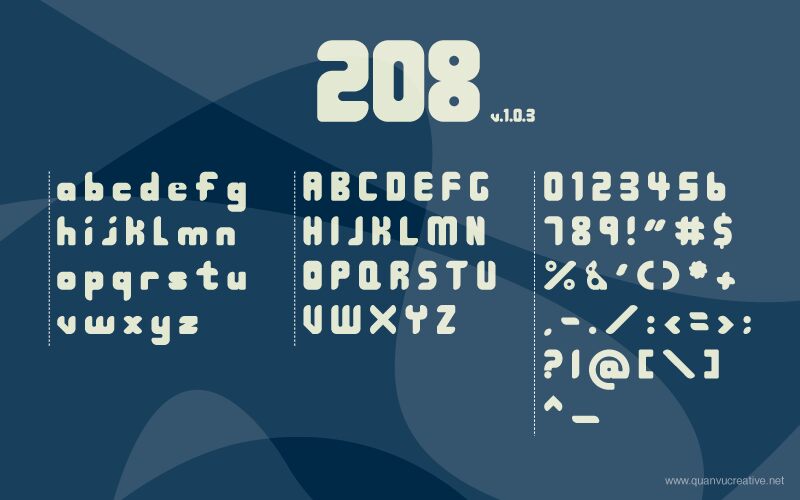
208 autorstwa Quan Vu to darmowy, modułowy font typu display o zdecydowanym, futurystycznym charakterze. Znaki zbudowano z ciężkich, „miękkich” bloków z wąskimi wycięciami i płynnymi łukami, co nadaje projektowi zabawkowej solidności, która mimo to pozostaje elegancka i nowoczesna.
Sprawdza się najlepiej tam, gdzie kilka przerośniętych znaków wykonuje całą pracę: na plakatach, okładkach muzycznych, grafikach sportowych, w identyfikacji wizualnej wydarzeń, nagłówkach czy opakowaniach, które wymagają odważnego, numerycznego akcentu. Jako darmowy krój, 208 jest szczególnie polecany do krótkich nagłówków, układów opartych na datach i dużych znaków graficznych – kształty są tak zwarte i rzeźbiarskie, że nawet krótkie słowo staje się pełnym pomysłem wizualnym.